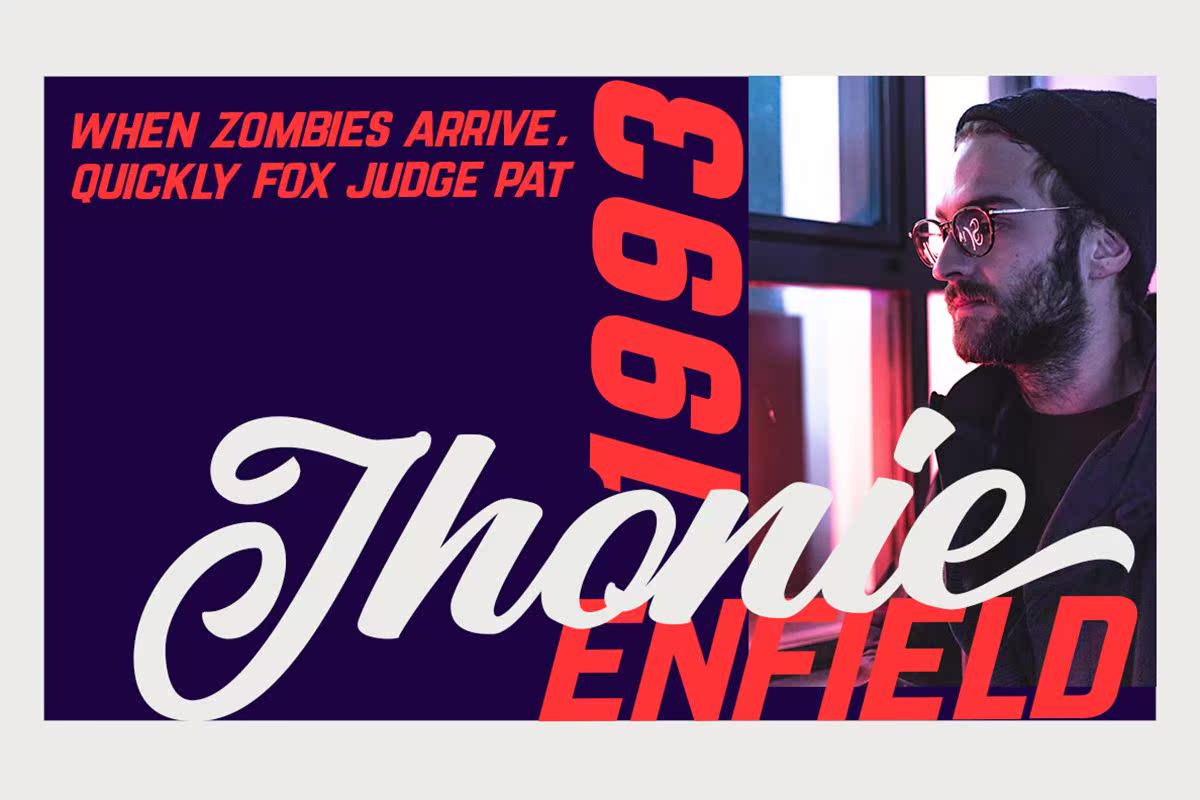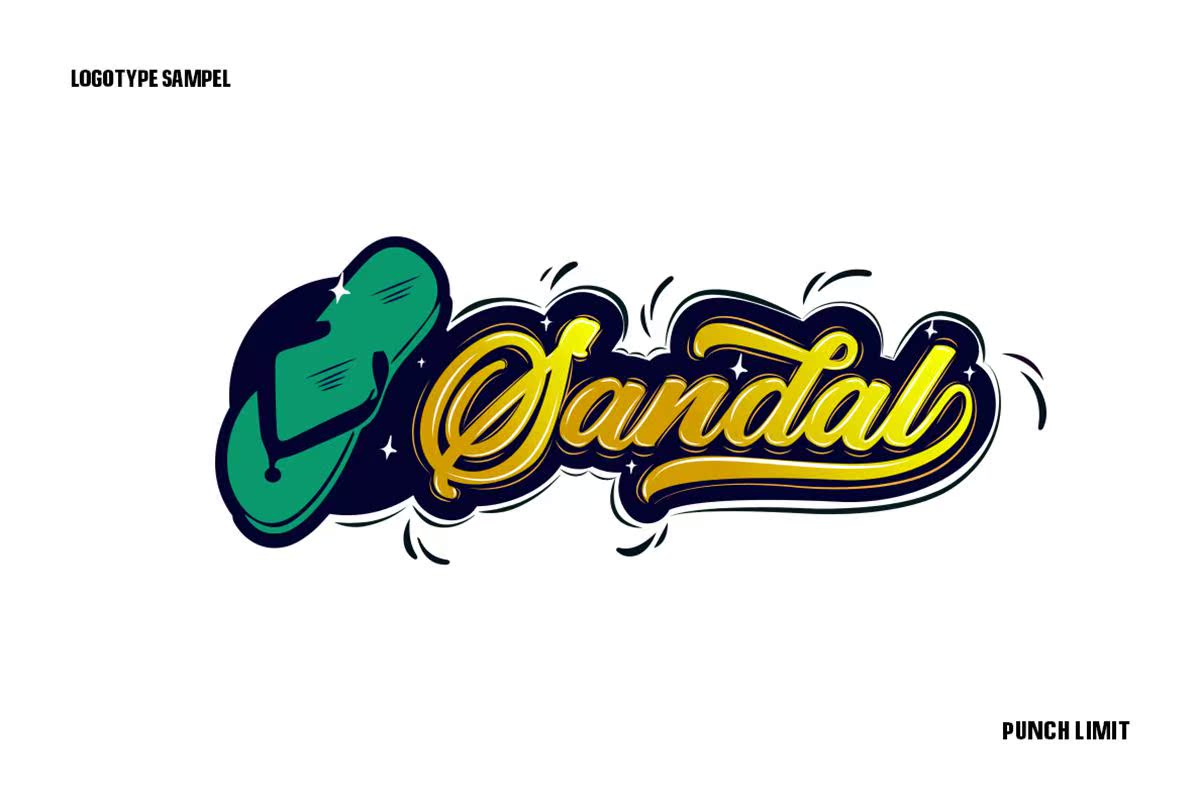
FreePunchLimitFontCombination是一种动态的Uofont,它能将巨大而持久的字体结合在一起。另外,它还将以一种独特的方式和一系列的努力完美地相互补充。它将在游戏、体育、设计、艺术等行业中表现得尤为出色,更重要的是,这种灵活的手写字体包括许多从不同的S01-SS15到每个大写字母的替代字体。它没有用处,因为任何东西都可以根据您的需要进行更改,并结合斜体和斜体,它看起来会追溯和经典。然而,这种自由字体具有100%的自由许可证,但只有两种格式。如果您想获得更多,请首先购买。